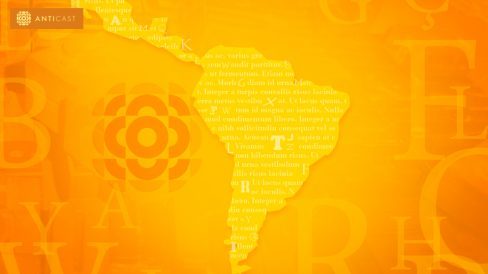
AntiCast 107 – Tipografia Latinoamericana: origens e identidade
Entrevista com Cecília Consolo
Neste programa, Ivan Mizanzuk e Henrique Nardi entrevistam Cecilia Consolo, organizadora do livro “La tipografia en latinoamérica: orígenes y identidad”, que aborda a história da tipografia na América Latina. Quais as origens? Quais as influências? Quais os impactos que o pensamento europeu (e de outras continentes) exerceu em nossas práticas? O livro, que será lançado em breve pela editora Blucher, buscará discutir essas questões de uma forma ainda pouco explorada no Brasil.